В чем секрет новых шрифтов Apple San Francisco
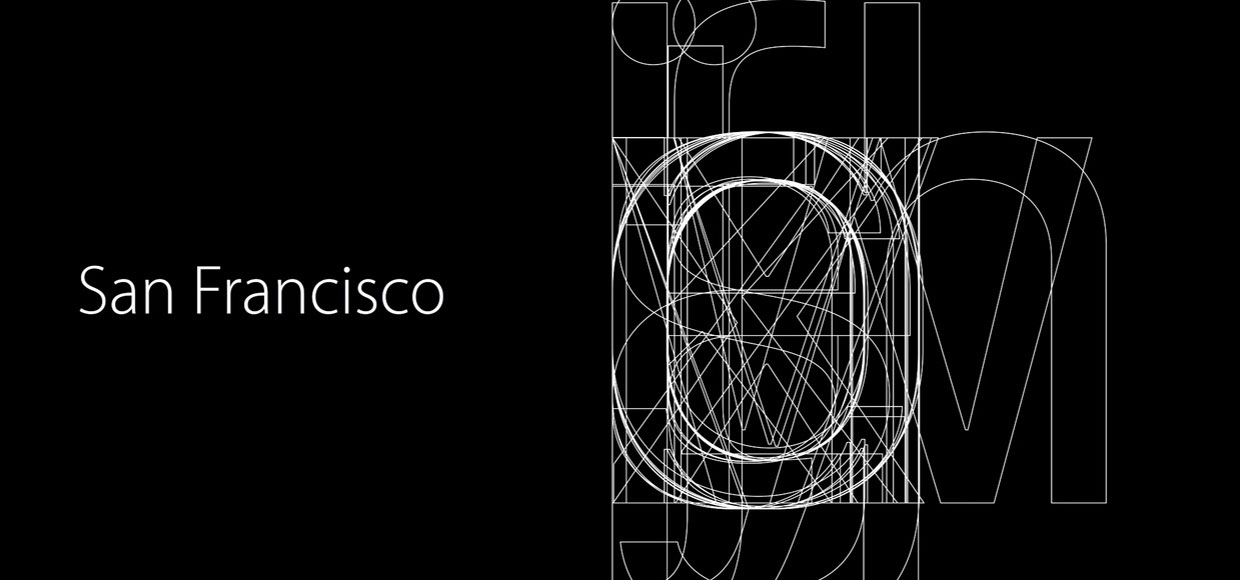
На самом деле таких секретов много и они будут интересны не только полиграфистам и адептам каллиграфии.
Релиз iOS 9 успешно состоялся, и одним из заметных нововведений стала замена шрифта в интерфейсе. Старый добрый Helvetica Neue сдал позиции шрифтам San Francisco. Они уже знакомы пользователям по Apple Watch, а теперь и вовсе стали стандартом для всех продуктов Apple — от iPhone до Mac.
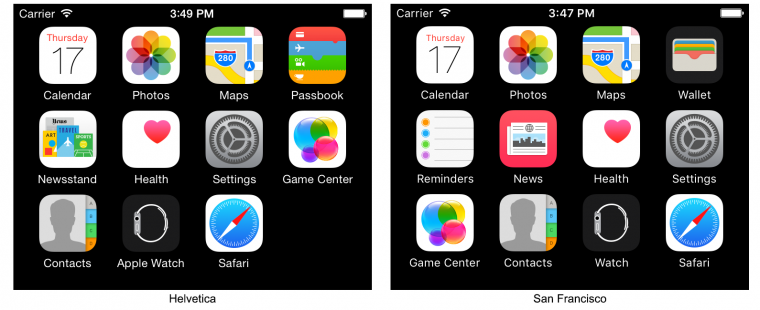
Шрифты Helvetica использовались Apple со времен первого iPhone. Причем, на Mac изначально использовался тип шрифта Lucida Grande, а Helvetica пришел ему на смену в OS X Yosemite 10.10. Но почему в руководстве компании вновь решили видоизменить привычный шрифт в интерфейсах мобильной и компьютерной ОС?
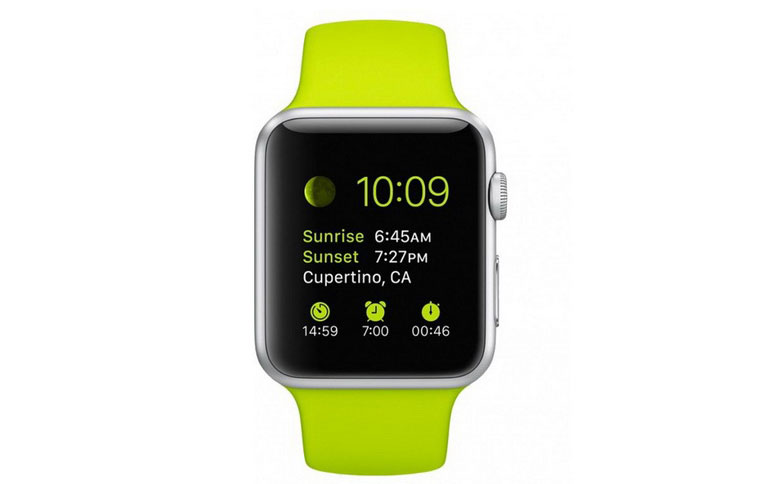
Helvetica плохо виден в мелком тексте
Оказывается, Helvetica совершенно не подходит для написания текстов мелким шрифтом. С переходом на этот шрифт в OS X Yosemite разработчики стали жаловаться на нечеткость текстов.
Вот пример, когда мелкий кегль шрифта Helvetica совершенно невозможно прочитать, текст просто сливается в одно мутное пятно. Говорят, что в Apple решили использовать шрифт San Francisco, чтобы пользователям было комфортно читать сообщения на Apple Watch.
Но ведь сегодня, за счет разрешения дисплеев смартфонов, читать на них контент порой проще и приятней, чем некоторые печатные тексты на бумаге. Да и дисплей iPhone гораздо больше, чем экран Apple Watch. Зачем же производителю было полностью переходить на использование San Francisco во всех продуктах — и в iPhone, и в iPad, и на Mac?
Шрифт San Francisco для iOS-устройств и компьютеров отличается
У San Francisco есть определенный ряд особенностей, которые делают данный шрифт более удобным в использовании в интерфейсах продукции Apple. Например, для Apple Watch используется один тип этого шрифта, а для iOS-устройств и Mac — другой. В частности, именно San Francisco применен в iOS и OS X, а для Apple Watch разработчики Apple выбрали San Francisco Compact. Отличаются они тем, что в SF Compact линии букв менее округлые, чем в стандартном SF.
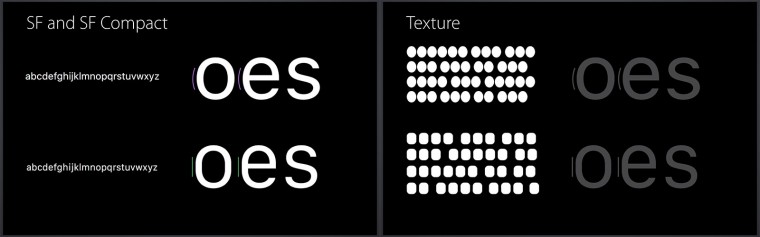
Благодаря такой разнице в текстах, написанных SF Compact, между буквами остается чуть больше места. Это и обеспечивает большую четкость текста на маленьких дисплеях Apple Watch.
К тому же, и SF, и SF Compact делятся еще на две подкатегории шрифтов — «Text» и «Display». Эту особенность в Apple зовут «оптический размер». Шрифты типа «Text» используются для совсем мелких текстов, а шрифты «Display» — для более крупных.
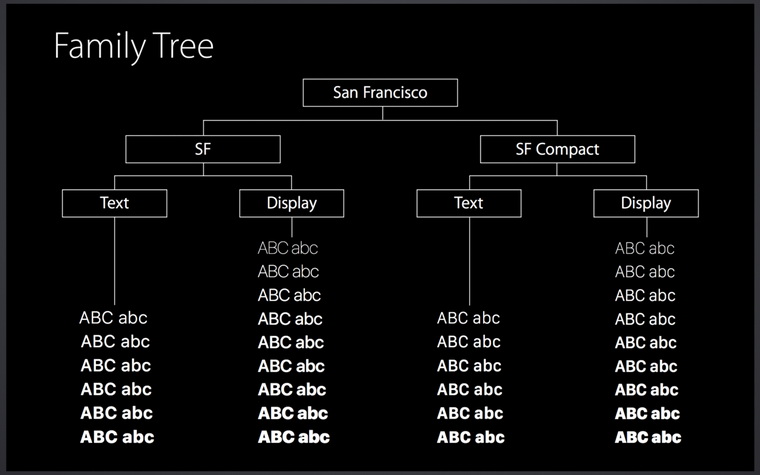
Как уже становится понятно, в рубленых шрифтах вроде Helvetica стоящие рядом буквы будто сливаются, а знаки «a», «e» и «s» вообще сложно отличить друг от друга в особенно мелком тексте.
В San Francisco, особенно в шрифтах для мелкого кегля «Text», подразумеваются бóльшие промежутки между буквами в словах, чем в шрифтах группы «Display». Да и сами слова выглядят чуть более растянутыми, что также облегчает их прочтение если использован мелкий шрифт.
Динамичность шрифтов San Francisco
Одна из лучших особенностей San Francisco заключается в том, как шрифт динамично оптимизирует свой рисунок. Система автоматически делает выбор между типами «Text» и «Display» в зависимости от размера текста. Так, тип шрифта 20 pt находится как раз на границе Text/Display.
Дизайнерам и инженерам не нужно думать о том, какой им использовать шрифт. Им просто нужно задать класс шрифтов UILabel, а система уже автоматически подберет подходящий шрифт.
Привлекает внимание и то, как в шрифтах San Francisco отображается двоеточие. Обычно оно располагается прямо на строке, а в SF этот знак препинания автоматически выравнивается, поднимаясь над строкой и становясь по центру между цифрами.
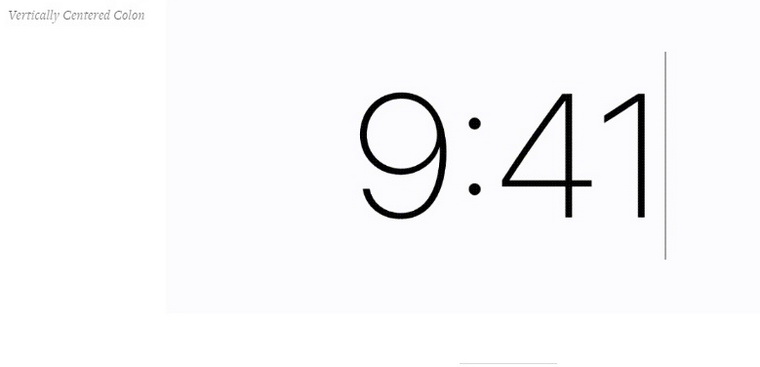
San Francisco – шрифт цифровой эры
Как мы можем видеть, шрифты San Francisco разработаны специально для удобства прочтения текста в любом размере и на любом устройстве.
Шрифт Helvetica был придуман в Швейцарии в 1957 году, когда электронных устройств и в помине не было. Сегодня он до сих пор используется как официальный шрифт во многих компаниях, и наверняка в будущем еще сохранится как своего рода классика.
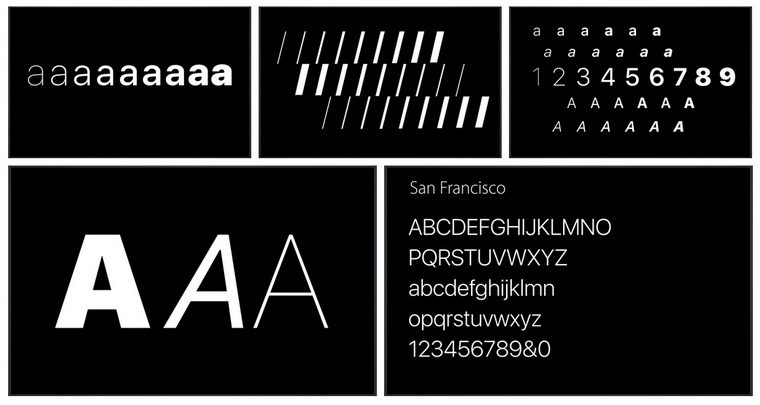
С другой стороны, San Francisco — шрифт современный. Он динамично меняет свой рисунок в зависимости от контекста. Его можно заслуженно считать одним из новых шрифтов уже исключительно цифровой эры. [Medium]
Я лично в восторге от San Francisco в iOS 9. По моим личным ощущениям картинка на iPhone стала восприниматься комфортнее в целом. Как-то более динамично, удобно — сложно выразить словами. С другой стороны, это явно дело вкуса, так как успел прочитать в Сети и немало негативных отзывов на новый шрифт. Что ж, каждому свое, как говорится. Помнится, я и от дизайна iOS 7 был в восторге (как и сейчас от iOS 9, в особенности понравилось повышенное количество анимации), а многие до сих пор с тоской вспоминают о скевоморфистской iOS 6.
Helvetica, на смену которой они пришли, была создана в Швейцарии в 1957 году, когда еще не существовало никаких цифровых устройств. Она, тем не менее, до сих пор используется многими компаниями в качестве корпоративного шрифта, и, вне всяких сомнений, будет использоваться и в будущем как хороший классический шрифт.
San Francisco же, напротив, является шрифтом современным. Его гарнитура меняется динамически, в соответствии с контекстом. Его можно назвать своего рода «родным шрифтом» цифровой эпохи.